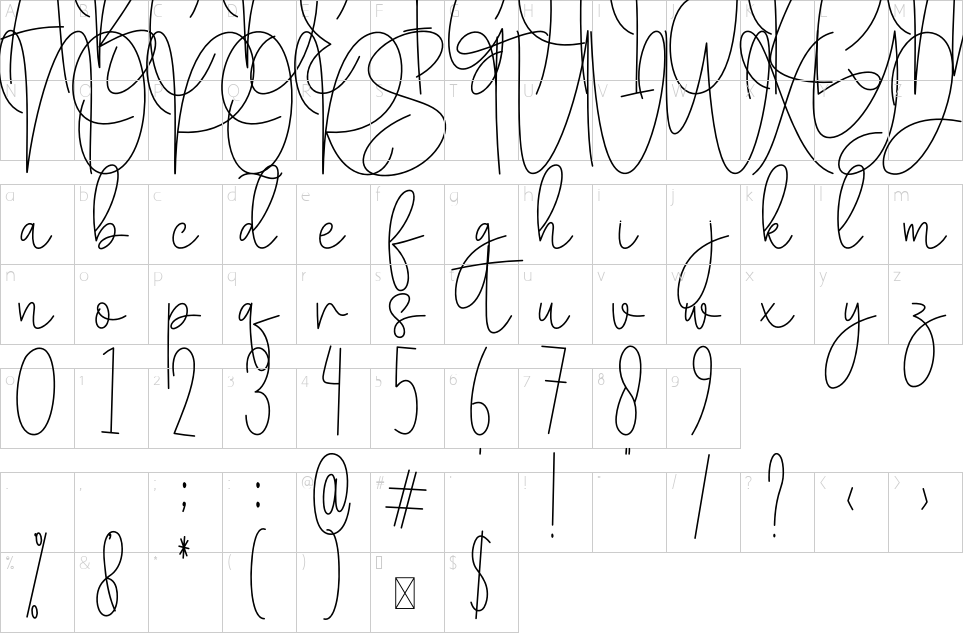
Aqui está uma descrição em português do Brasil, envolvente e natural, para a página de download da fonte “Monday Font | 1001 Free Fonts”: Aqui está uma fonte de gráficos gratuita e versátil que vale a pena explorar. A fonte “Monday” é um design minimalista e moderno criado por scratchones, disponível para quem busca uma solução prática e de alta qualidade. Se você está procurando por uma fonte para títulos, listas de texto ou até mesmo para textos de e-mail, essa é a escolha certa. “Monday” oferece uma aparência limpa e fácil de ler, ideal para criar designs profissionais e modernos. Com uma fácil adaptação para Windows e Mac, esta fonte é uma ótima opção para quem busca uma fonte gratuita de qualidade. Descubra por que “Monday” é uma fonte indispensável para seu portfólio de design.